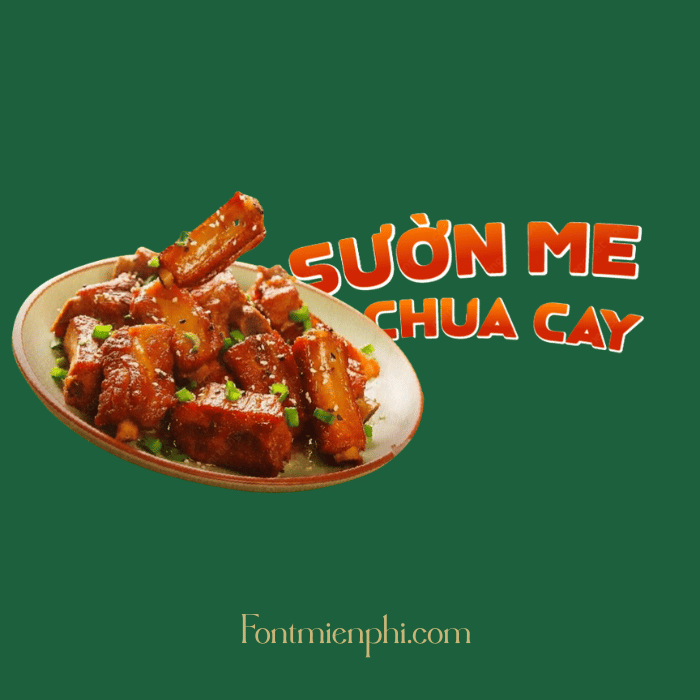
Font Việt hóa 1FTV VIP Bluffolk
Font Việt hóa 1FTV VIP Bluffolk – Phong Cách Độc Đáo, Thiết Kế Chuyên Nghiệp
Font Việt hóa 1FTV VIP Bluffolk là một trong những font chữ đẹp, độc đáo được nhiều designer yêu thích. Với kiểu chữ cá tính, nét thanh – đậm rõ ràng, Bluffolk phù hợp cho thiết kế logo, banner, poster, hoặc các dự án sáng tạo đòi hỏi phong cách mạnh mẽ. Font hỗ trợ đầy đủ bảng mã Tiếng Việt, giúp người dùng dễ dàng sử dụng mà không lo lỗi font.
Đặc điểm nổi bật của 1FTV VIP Bluffolk:
✔ Thiết kế độc quyền – Nét chữ sắc sảo, phù hợp thiết kế hiện đại.
✔ Hỗ trợ Tiếng Việt – Đầy đủ dấu, tương thích với mọi phần mềm thiết kế.
✔ Đa dạng ứng dụng – Dùng cho in ấn, quảng cáo, social media, branding.